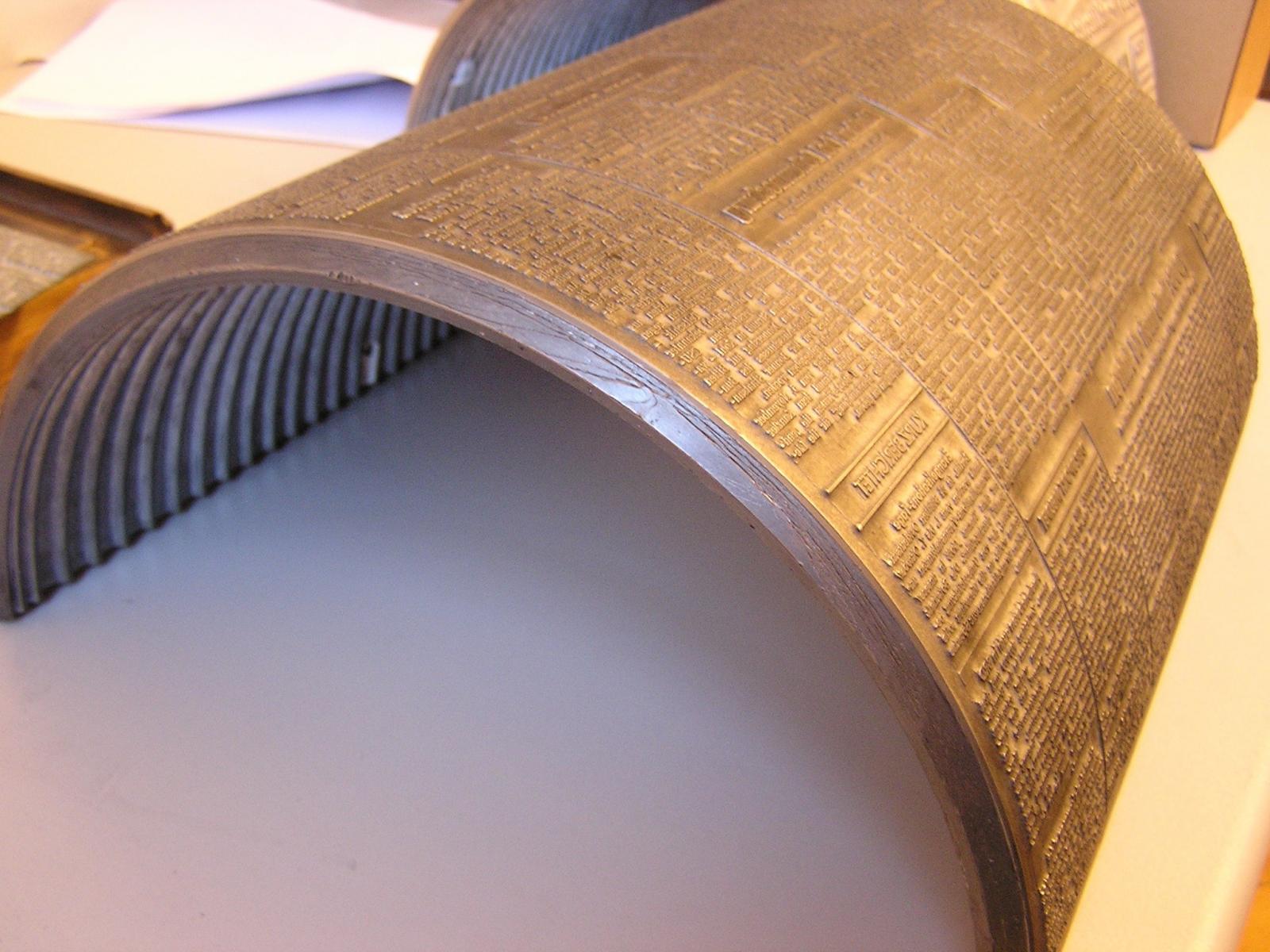
Fragen zur Stereotypie
Von den Zeitungsseiten wurden zu Bleisatz-Zeiten Pappmatern angefertigt, von denen dann ein Rundstereo gegossen wurde. Als »Prägefest« bezeichnete man Schriften, die den Druck der Prägepressen bei der Maternherstellung standhielten. Die Grundschrift der Braunschweiger Zeitung beispielsweise war die »Candida«. Sie galt ebenfalls als »prägefest«.
Ich weiß, dieses Thema ist uralt, aber ich habe es beim Stöbern im Forum gefunden, ich habe dabei was gelernt (nämlich wie eigentlich eine Druckform für eine Rotationspresse entsteht), aber es ist eine neue Frage aufgekommen: Mit welchem Material wurde da gearbeitet. Dass der Satz mit z.B. der Linotype-Maschine in Letternmetall passierte, ist klar. Aber was passierte dann? Wurden die gesetzten Zeilen wirklich mit Pappe abgeformt um die Matern herzustellen? Und woraus wurden dann die Stereos gegossen? Wieder mit Letternmetall? Hält Pappe das aus? Die müsste doch bei der Schmelztemperatur des Letternmetalls schon fast anfangen zu brennen, oder nicht?